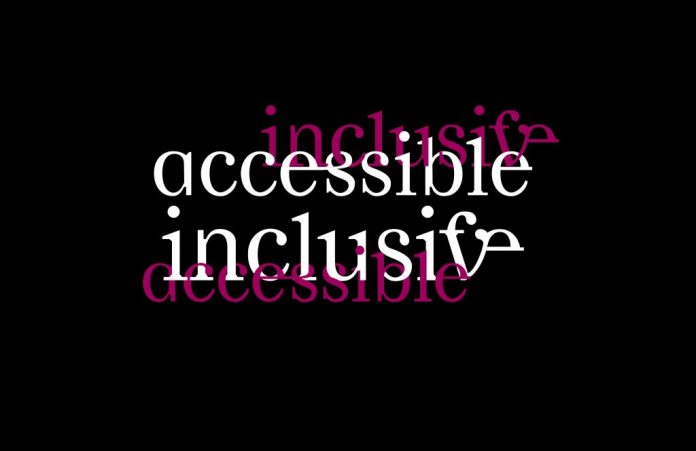
Écriture et typographie inclusives : obstacle pour les personnes dys ?
L’usage de l’écriture et des typographies inclusives se développe dans les communautés féministes et queer, ainsi qu’au-delà. Parmi les critiques adressées à ces outils, la difficulté de lecture qu’ils posent pour les personnes dys (dyslexiques, dyspraxiques, dysorthographiques, etc.) revient régulièrement. Diplômée d’un DNA de l’EESAB Rennes, étudiante en DNSEP et membre de Bye Bye Binary, Sophie Vela entreprend une étude exploratoire dans le but de recueillir les retours de personnes dys par rapport à l’écriture et à la typographie inclusives.
Multiplicité des écritures et typographies inclusives
Loin de prendre qu’une seule forme, l’écriture inclusive se caractérise par une multiplicité de solutions et d’usages, permettant d’inclure à la fois le masculin et le féminin. Parmi les différents procédés d’écriture, on distingue ceux qui relèvent d’une gymnastique de la langue comme le doublet ou l’usage de termes épicènes, les procédés de féminisation de termes masculins, notamment les noms de métiers, l’usage de signes typographiques insérés pour signifier un double accord (point, point médian, tiret quart-de-quadratin, slash, parenthèses, capitale, apostrophes, et ligatures expérimentales…), ou encore l’usage d’accords alternatifs (inclusixinclusi*libérae…). Sophie Vela, diplômée d’un DNA de l’EESAB Rennes et membre de Bye Bye Binary, mène une recherche à ce sujet. Dans son mémoire de recherche “Avez-vous pensé aux marges ?” autour de l’écriture et de la typographie inclusives, elle précise que ces procédés soulèvent certaines problématiques propres à la typographie. “L’utilisation de caractère éloignant les lettres (tiret, barre oblique) altère fortement le gris typographique” affirme-t-elle. Le détournement de signes typographiques, comme le tiret ou encore l’astérisque, faisant l’objet d’un autre usage que celui initial, peut aussi mettre en cause la compréhension du texte.
L’argument de la dyslexie
Au-delà de ces enjeux, propres aux difficultés de l’expérimentation permettant de développer de nouvelles solutions pour une meilleure inclusivité, un argument contre les écritures et les typographies non-binaires est récurrent. Celles-ci ne seraient pas inclusives pour les personnes dys. Ces dernières ont des fonctionnements atypiques pouvant causer des difficultés à comprendre ou à produire la parole et le langage, ou à l’utiliser en contexte pour communiquer. Si la Fédération Française des DYS “met en cause la masculinisation de la langue française tout en déconseillant l’utilisation du point médian pour les jeunes dyslexiques” précise Sophie Vela, la Fédération Nationale des Orthophonistes ajoute manquer d’études scientifiques sur le sujet. Enfin, le Réseau d’Etudes Handi-Féministes se positionne “contre la récupération du handicap par les personnes anti écriture inclusives.”
Afin de recueillir la parole des concerné·es au sujet des obstacles que pourraient engendrer l’écriture et la typographie inclusives, Sophie Vela entreprend une étude exploratoire. Elle est inspirée de premières recherches menées par la•e graphiste Camille Circlude et l’orthophoniste Christella Bigingo. L’étude vise à tester la possibilité de compréhension sémantique et la lisibilité de 24 courtes phrases composées et rédigées de telle façon à présenter un grand nombre d’occurrences de solutions d’écritures inclusives. L’échantillon de l’étude rassemble 140 volontaires de 16 à 60 ans, 70 personnes dys et 70 personnes non dys, qui ont répondu au questionnaire. Dans le cadre de cette étude, Sophie Vela utilise les typographies inclusives BBB Baskervvool, le BBB BNM de Bye Bye Binary, le Times New Roman Inclusif d’Eugénie Bidaut, l’Homoneta de Quentin Lamouroux, ainsi que le DIN dong de Clara Sambot.
Entre difficultés partagées et habitude
L’étude exploratoire de Sophie Véla montre qu’en ce qui concerne la compréhension sémantique  celle du sens du mot et de la phrase , 95% des propositions ont été saisies au total. Les phrases qui ont posé des difficultés sont les mêmes pour les deux groupes et mobilise uniquement des ligatures. Si les personnes dys ont plus de difficultés de compréhension que les personnes non dys, l’écart de difficulté de compréhension se situe entre 2% et 13% pour ces trois phrases. En termes de lisibilité  le déchiffrage de la lettre , 20% des phrases ont causé une difficulté pour les personnes dys, 13% pour les personnes non dys. Ce sont notamment les ligatures inclusives qui ne sont pas évidentes à lire, d’autant plus que cette forme expérimentale d’écriture est peu répandue dans l’usage et donc peu apprise à être lue. Si les difficultés pour les personnes dys sont plus nombreuses, elles ne leur sont donc pas propres.
Une autre étude, “De la nécessité d’étudier l’accessibilité des écritures inclusives aux personnes dyslexiques“, menée par Justine Bulteau, étudiante à l’ENSC de Bordeaux, École Nationale Supérieure de Cognitique, fait le constat que les personnes ayant le plus de difficultés avec la lecture de l’écriture inclusive “possèdent des caractéristiques comme un positionnement très défavorable ou défavorable aux écritures inclusives, une faible voire inexistante habitude à ces écritures et une lecture de 1h à 3h par jour. Le genre associé de ces individus est masculin”. Les personnes ayant le plus de facilité avec la lecture de l’écriture inclusive ont “des caractéristiques comme un positionnement très favorable ou favorable aux écritures inclusives, une forte habitude à ces écritures et une lecture de 5h à 10h par jour. Les genres associés de ces individus sont non-binaire, féminin et agenre”. Sophie Vela remarque aussi que les difficultés de lecture de l’écriture inclusive découlent d’un manque d’apprentissage de la part des personnes non dys, mais aussi dys. Comme l’affirme l’un des enquêtés, “tout ce que j’arrive à lire, c’est parce que je l’ai appris en séance d’orthophonie. Si, durant mes séances, j’avais découvert l’écriture inclusive, je n’aurais aujourd’hui aucun mal à la lire. Certes, cela me demande donc des efforts, mais ça en vaut la peine pour inclure tout le monde”. Pour Sophie Véla, si les ligatures expérimentales posent des difficultés, elles sont néanmoins une forme d’écriture inclusive intéressante, car elles permettent de ne pas couper un mot par des signes typographiques comme le point médian ou le tiret. Son usage est aussi politique : elles incarnent l’idée de lien et de transition, à l’inverse du point médian qui induit une séparation entre les deux genres, masculin et féminin.
Les difficultés de lecture de l’écriture et des typographies inclusives relèvent donc aussi d’un enjeu d’apprentissage et d’usage. Le point médian est presque aussi bien lu et compris par les personnes non dys que celles dys, car entré dans les usages. Mais, si les ligatures expérimentales causent plus de difficultés à des personnes dys qu’à celles non dys (tout comme tout exercice de lecture), elles s’inscrivent dans une volonté d’expérimentation post-binaire politique. “Chercher à rendre la langue française accessible aux personnes dys est un travail qui, d’une part, mérite tout notre intérêt et, d’autre part, ne doit pas servir à évincer d’autres réformes linguistiques, telles que l’écriture inclusive, permettant de lutter contre d’autres discriminations, en l’occurrence le sexisme” affirme notamment le Réseau d’Etudes Handi-Féministes… Le collectif interpelle les fabricants de lecteurs d’écran : leurs produits doivent être en capacité de déchiffrer correctement ces nouvelles formes de langage et d’écriture. Sophie Vela invite d’autres personnes à poursuivre son travail de recherche exploratoire, en incluant notamment des exercices de lecture de textes plus long et en constituant un échantillon plus large. Elle s’attache à présent à essayer de développer des formes de ligatures permettant une lecture facilitée et instinctive.